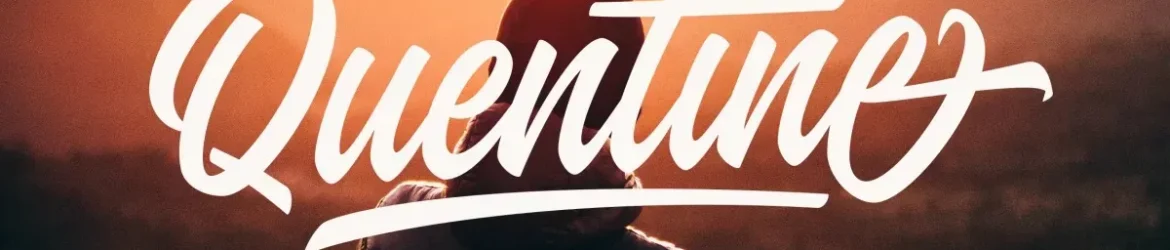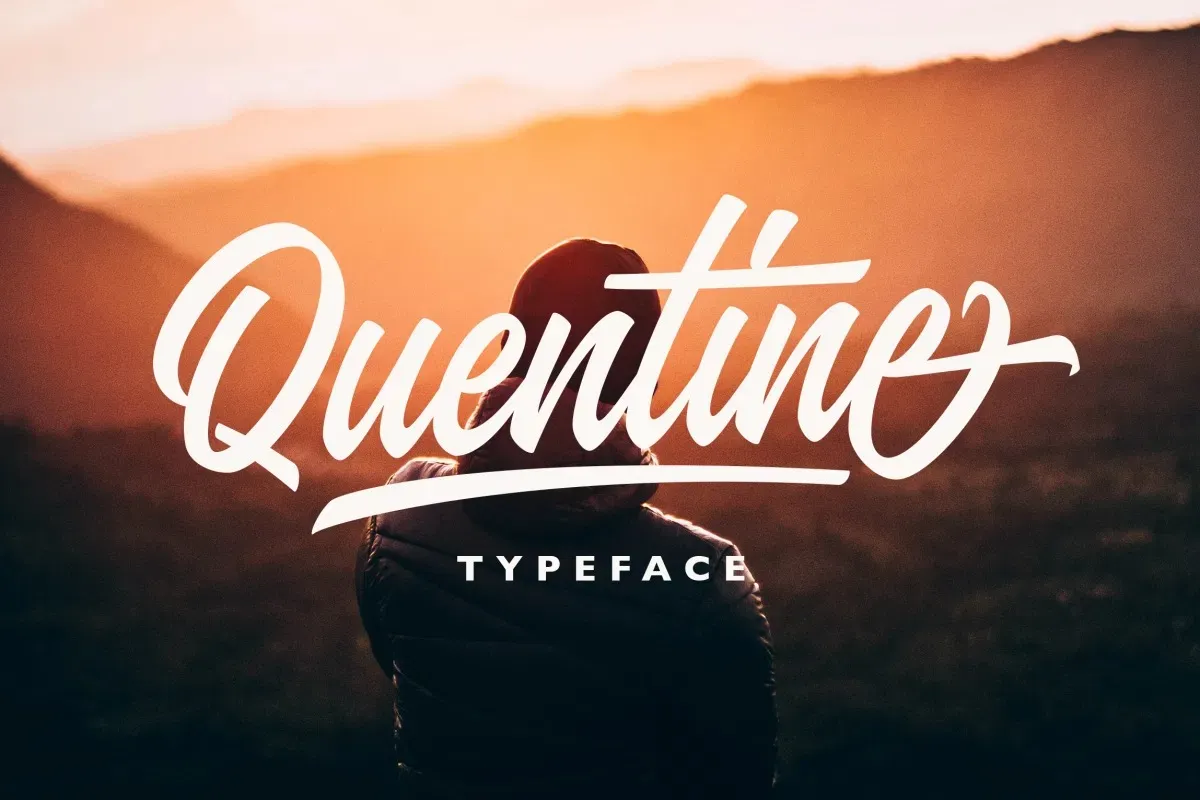
Quentine Font – Fonte Grátis
Quentine Font
Aqui está uma versão em português do Brasil para a descrição da fonte Quentine Font, seguindo as regras fornecidas: A fonte Quentine é uma escolha perfeita para aqueles que buscam um script elegante e sofisticado. Desenvolvida por Get Studio, esta fonte vem com diversas opções de estilos alternativos para cada letra, o que a torna versátil e capaz de trazer vida a vários tipos de materiais gráficos. Ideal tanto para criação de logotipos, tags de nomes, frases ou citações, embalagens de produtos, material de merchandising, mídia social e cartões de convite, Quentine combina elegância com funcionalidade. O conjunto completo de letras minúsculas e maiúsculas, caracteres alternativos, uma ampla gama de pontuações e números numéricos, e suporte multilíngue completam este produto. O destaque deste font é a sua capacidade única de alterar o visual das letras sem perder a consistência do design. Essas opções variadas foram organizadas através da utilização de vários recursos OpenType, incluindo Alternâncias Estilísticas, Conjuntos Alternativos e Ligaturas. Quentine é uma excelente opção para designers que desejam dar vida aos seus projetos com um tipo personalizado e sofisticado. Sem dúvida, é a fonte perfeita para estilos de design moderno e criativo.